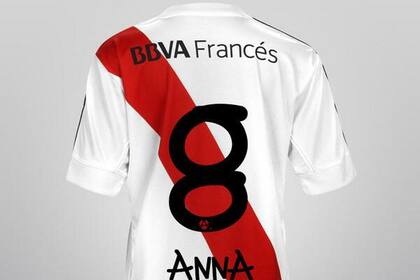
El próximo miércoles, en la revancha ante Lanús, por los cuartos de final de la Copa Sudamericana, River estrenará tipografía en su camiseta. En un gran acto de integración, la casaca millonaria contará con los números creados por la joven catalana Anna Vives.
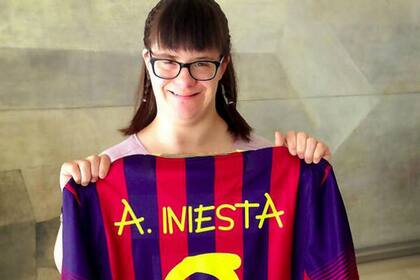
La acción, que cuenta con el apoyo de la Fundación Evolución, significa "un mensaje positivo sobre las capacidades de las personas con síndrome de down", explican desde la fundación. Y no será la primera vez: Barcelona estrenó los números de Anna en el último Trofeo Gamper. Allí, Anna ingresó al campo de juego de la mano de Andrés Iniesta, su ídolo.
Los rumores indican que Anna vendrá a Buenos Aires para mostrar la camiseta de River, con el número 8, su favorito, en el Monumental, pero todavía no existió confirmación sobre su presencia.
La tipografía Anna. Anna es una tipografía en formato digital diseñada por Anna Vives, una chica con capacidades diferentes que dedicó un año a acercarse al mundo de la letra, trabajando la lectura y la escritura. La intención original de la tipografía es imitar los trazos de la escritura de Anna, que mezcla caracteres en mayúscula y minúscula indistintamente. Se puede descargar en annavives.com.